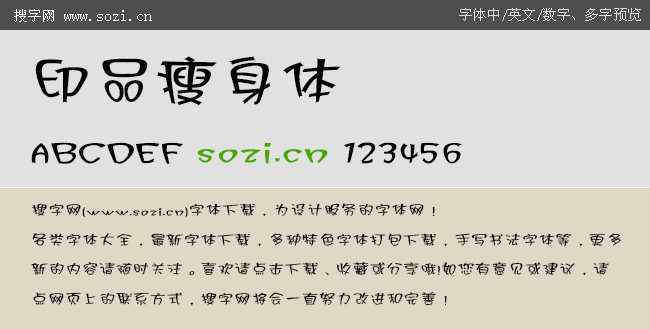
印品瘦身體
搜字網(wǎng)給大家提供一款印品瘦身體中文字體下載,該字體結(jié)構(gòu)圓潤(rùn)有型、別致可愛(ài),上寬下窄的二次元風(fēng)格,充滿了減肥般的樂(lè)趣。適用于海報(bào)設(shè)計(jì)、包裝設(shè)計(jì)、商業(yè)廣告等廣告設(shè)計(jì)。